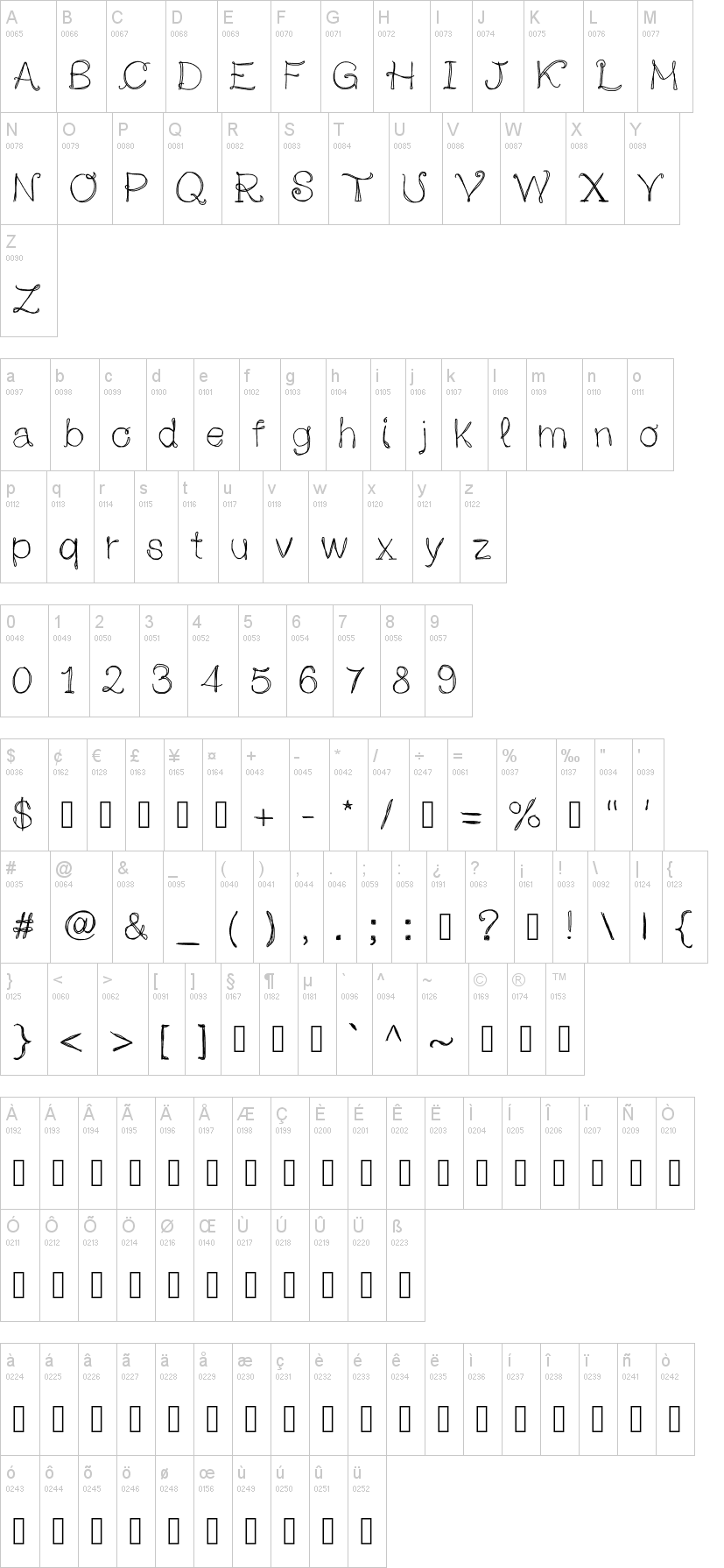
A Day In Autumn 字体是一款温暖的、抒情的草书字体,它具有传统的草书风格,同时也刻意地融入了西方的现代感。它的字体结构紧凑,笔画细腻,给人以一种温暖而又充满情感的感觉。它还具有可定制的功能,可以根据不同的需求调整字体的大小、宽度等参数,使其适应不同的场景。内容介绍
A Day In Autumn是一款非常不错的手写艺术字体,具有很好的视觉感,适合于文化类的宣传设计、商业类品牌的广告和产品包装设计以及个性化文字排版等较多场景。